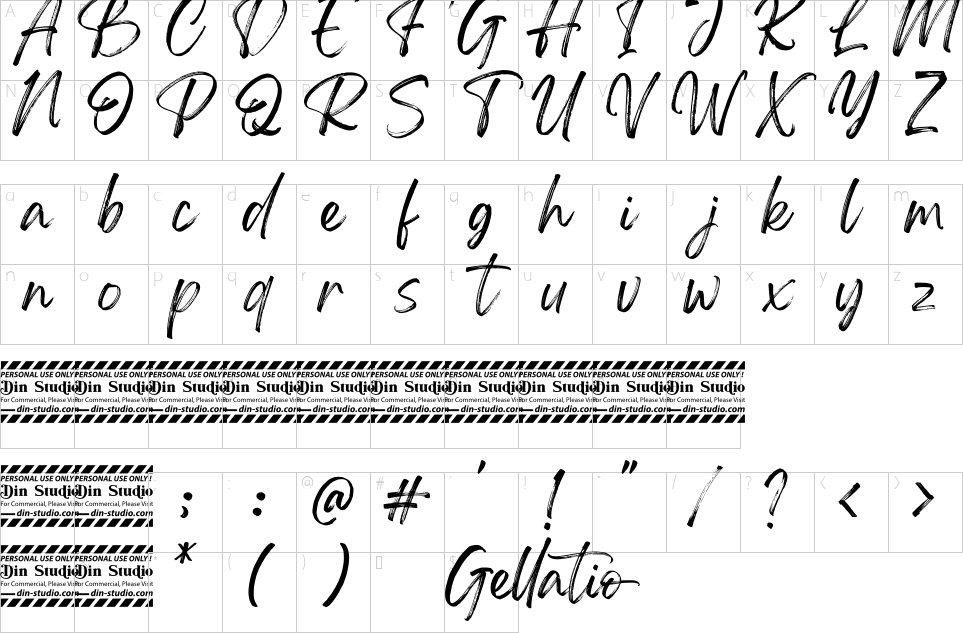
Gellatio Font – Download Grátis
Descubra a beleza única da Gellatio Font, uma fonte de graça disponível tanto para Windows quanto para Mac. Cada caractere desta elegante e fluida fonte foi cuidadosamente desenhada pela Din Studio. Com seu design refinado e moderno, a Gellatio é perfeita para criar textos com graciosidade e sofisticação. Sua fácil legibilidade torna-a ideal tanto para designers digitais quanto para aqueles que simplesmente desejam adicionar um toque autêntico às suas criações digitais. Com 2,913 downloads já registrados, é evidente a popularidade desta fonte. Adquira a sua e transforme as suas obras de arte digitais no topo do seu campo.